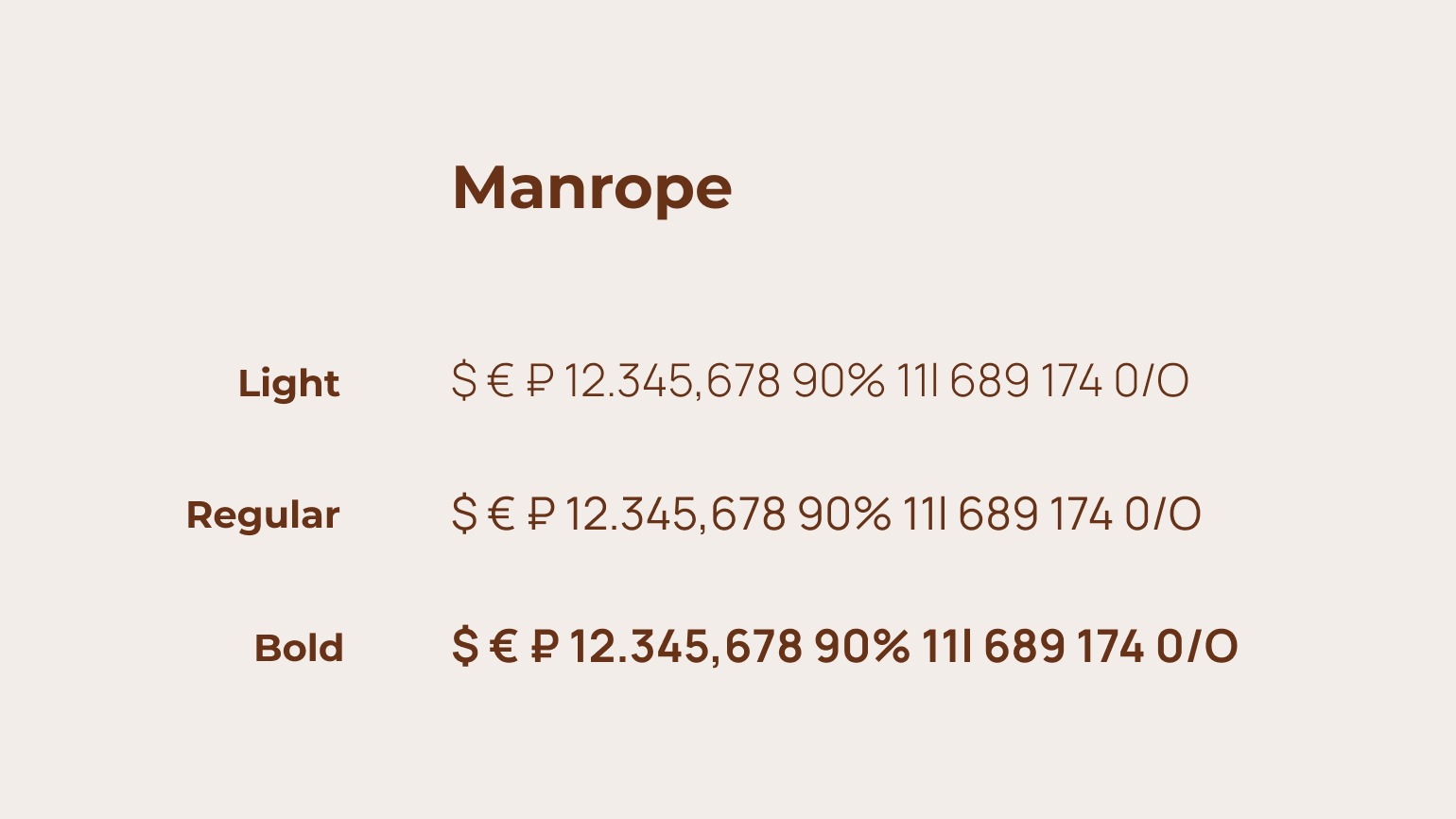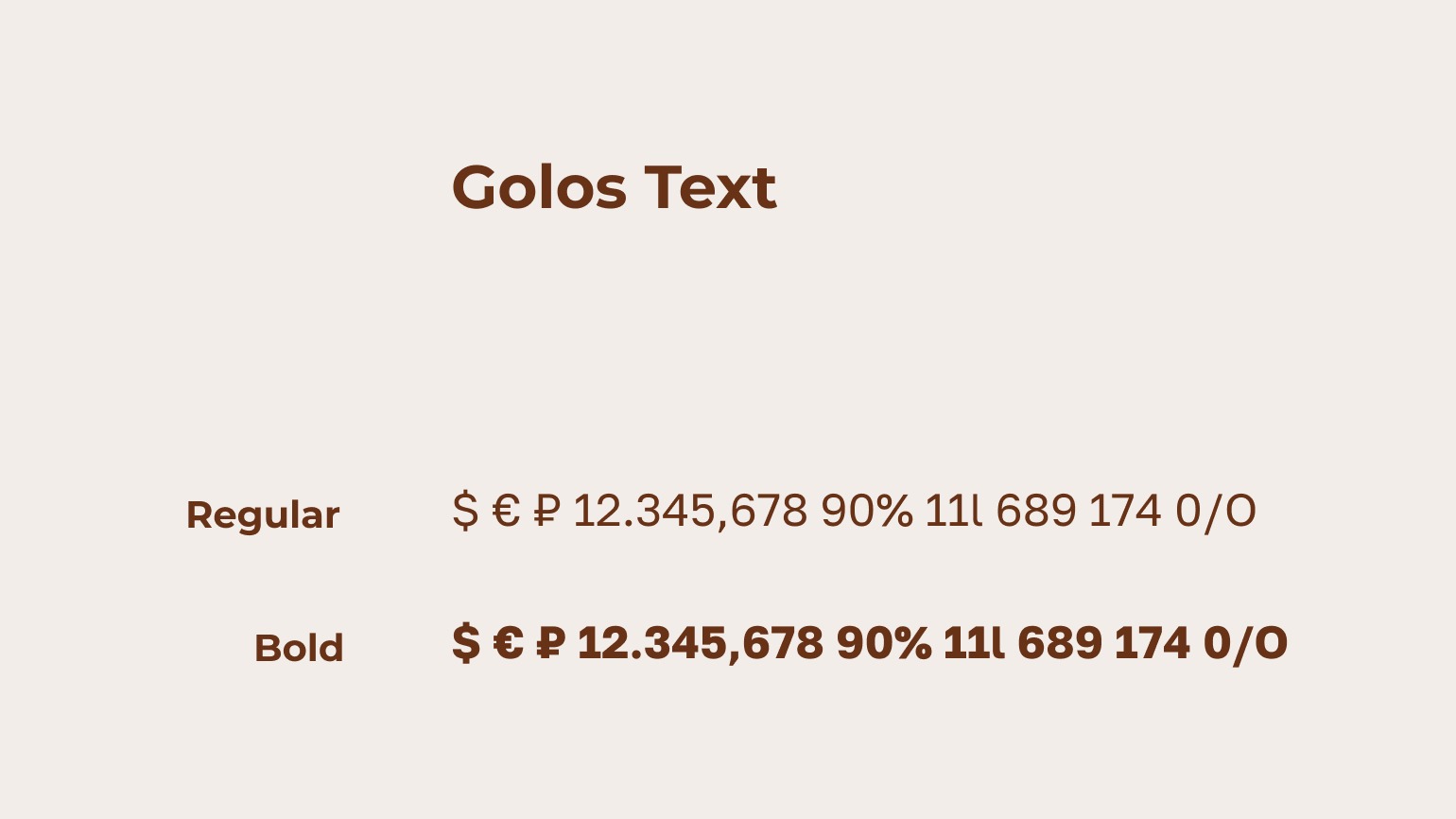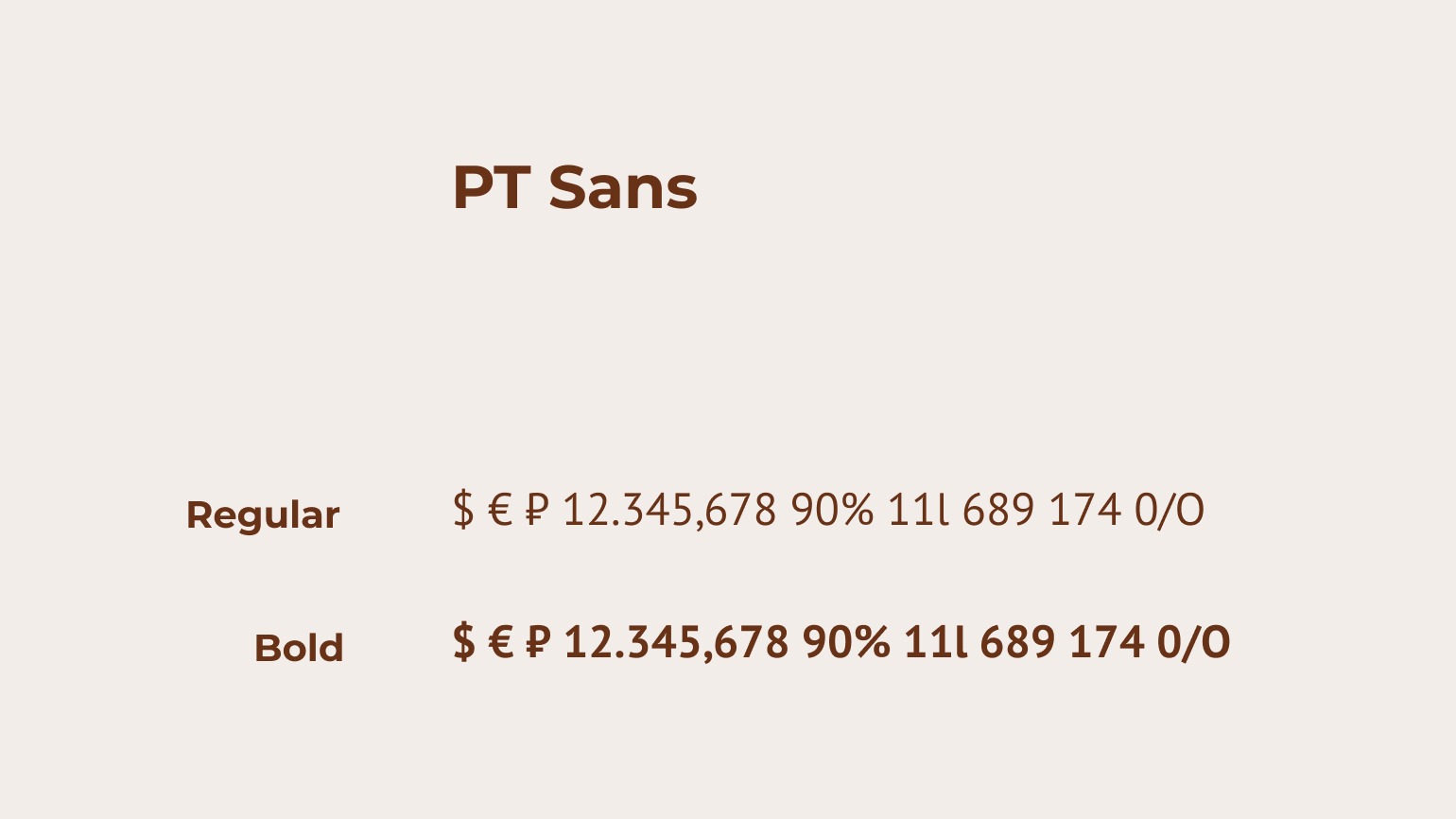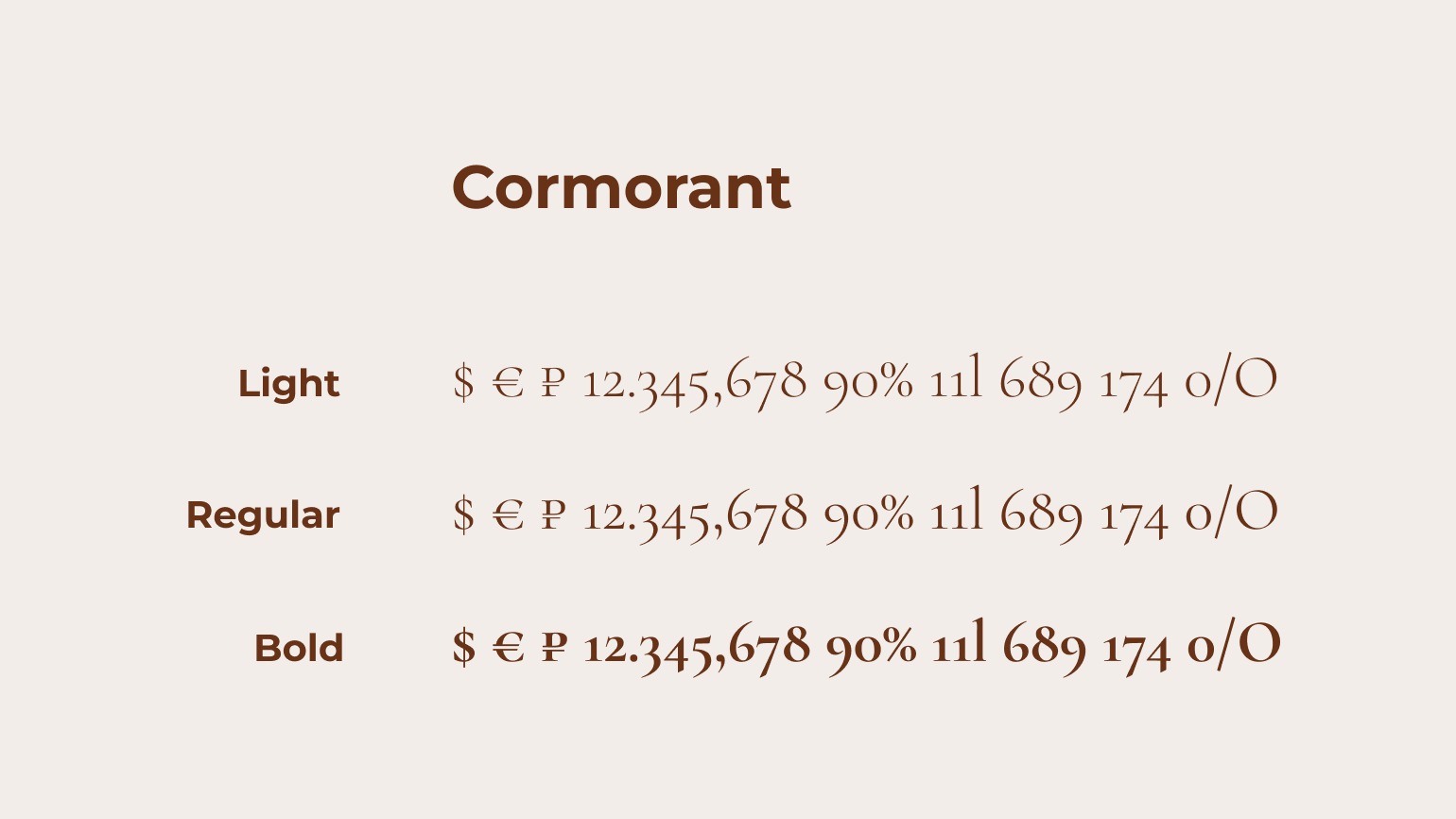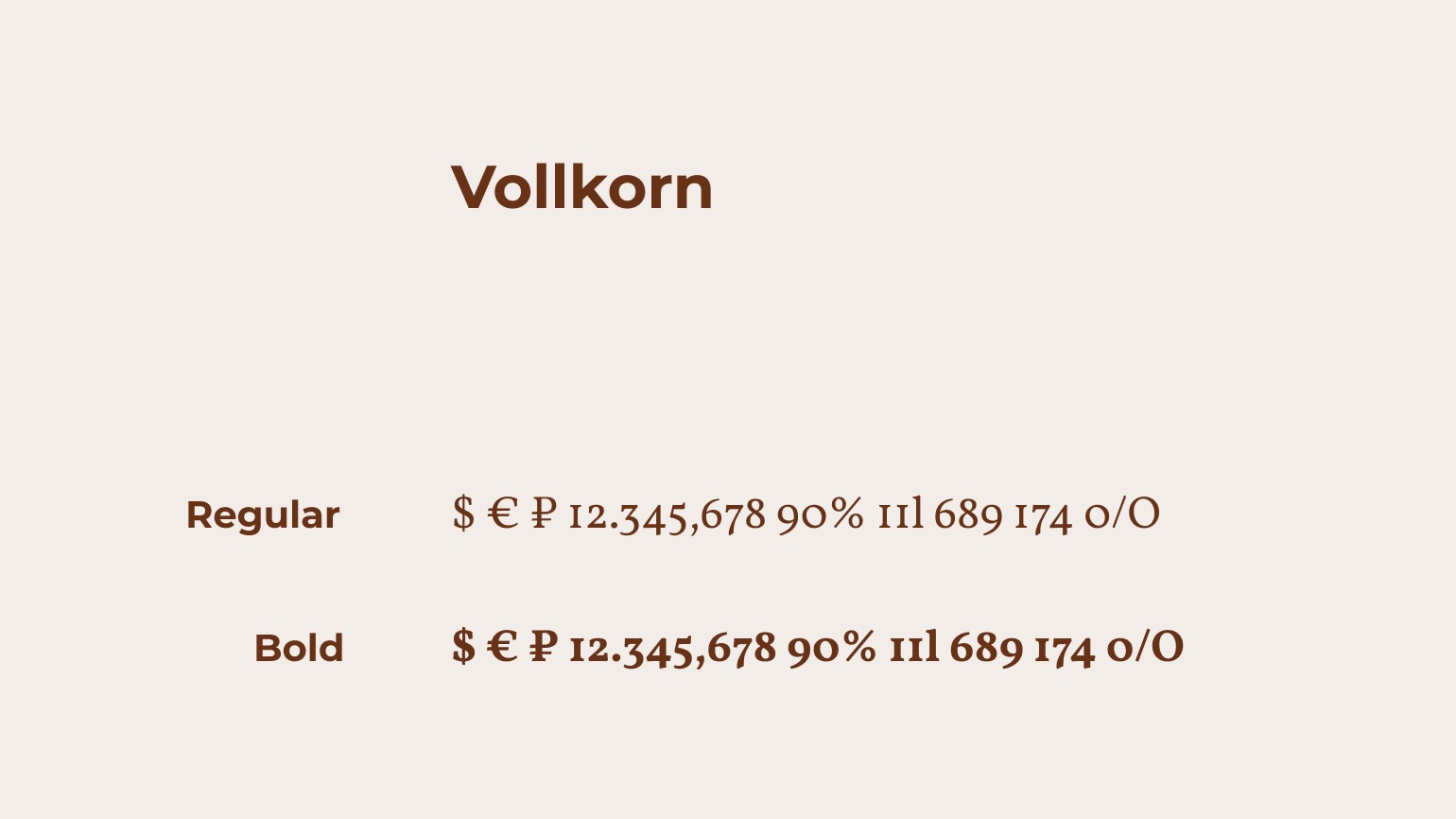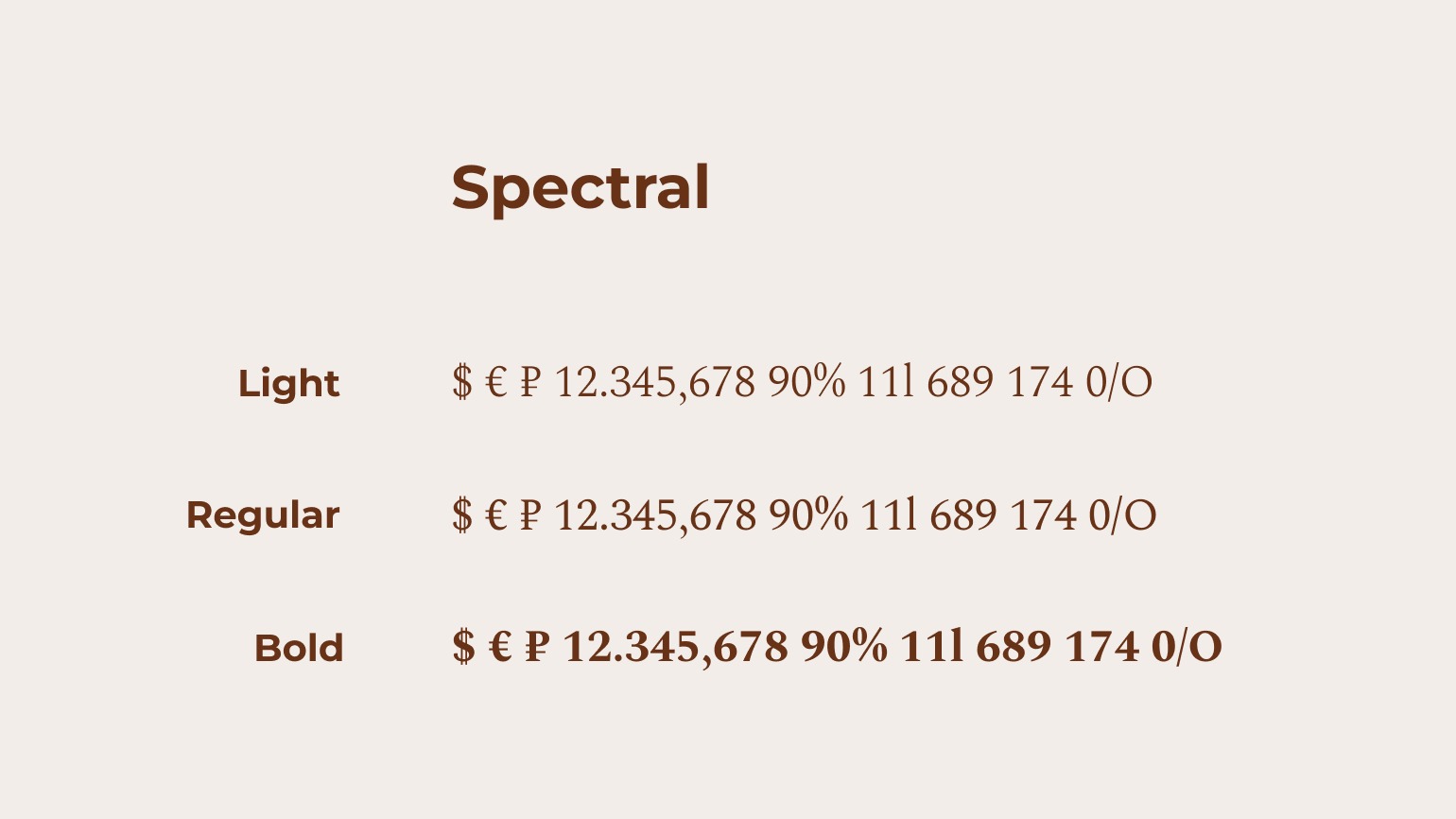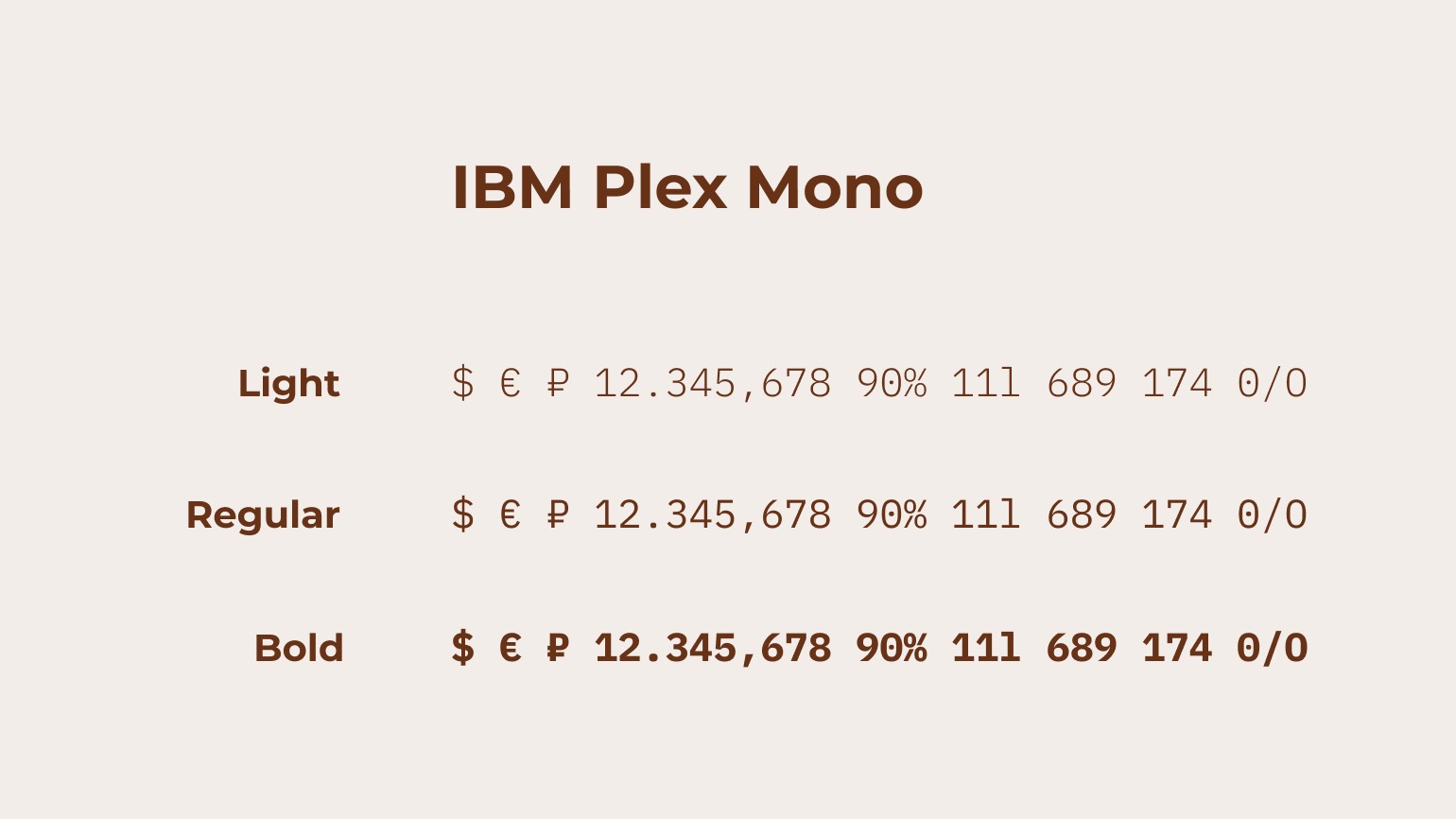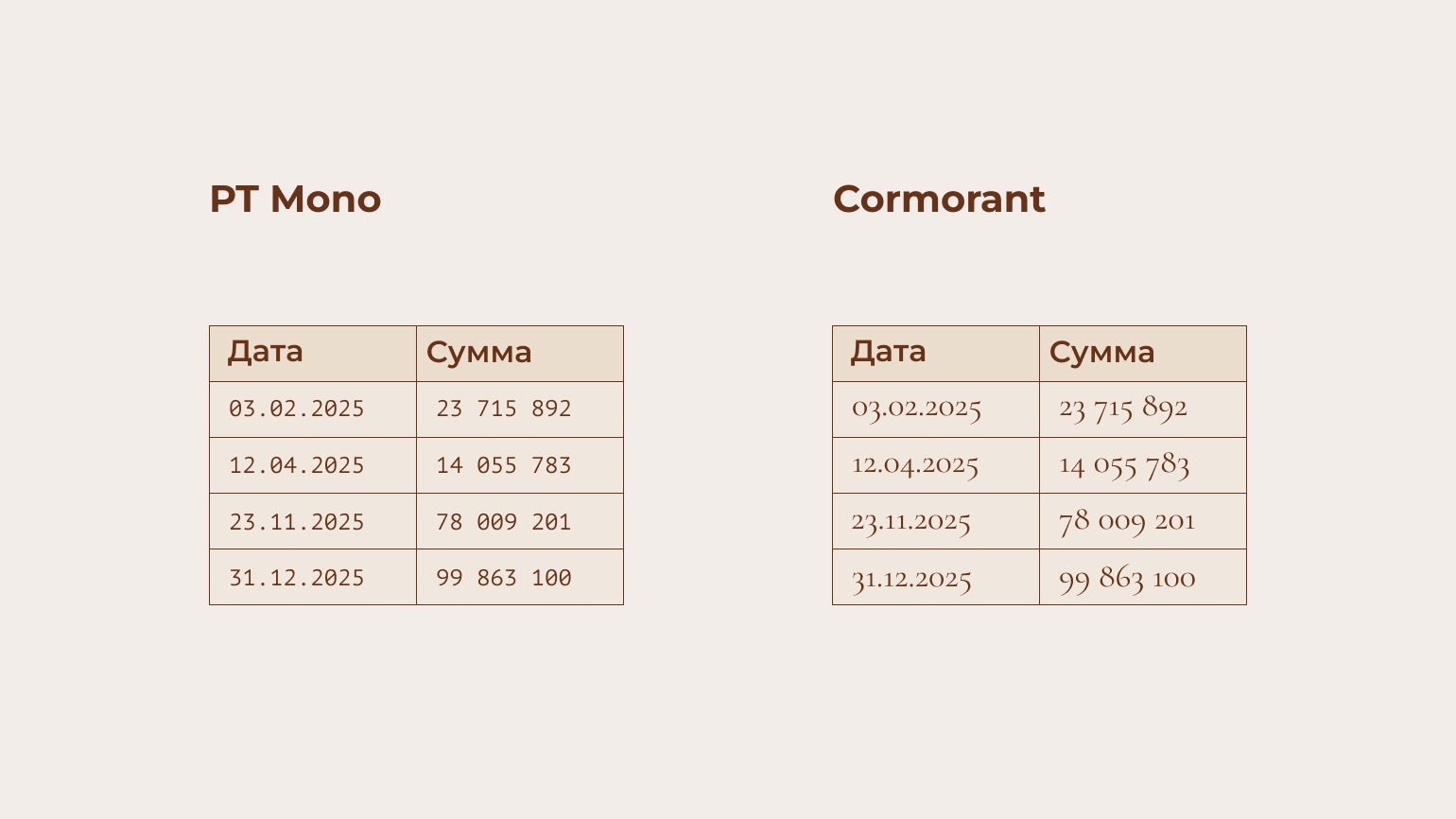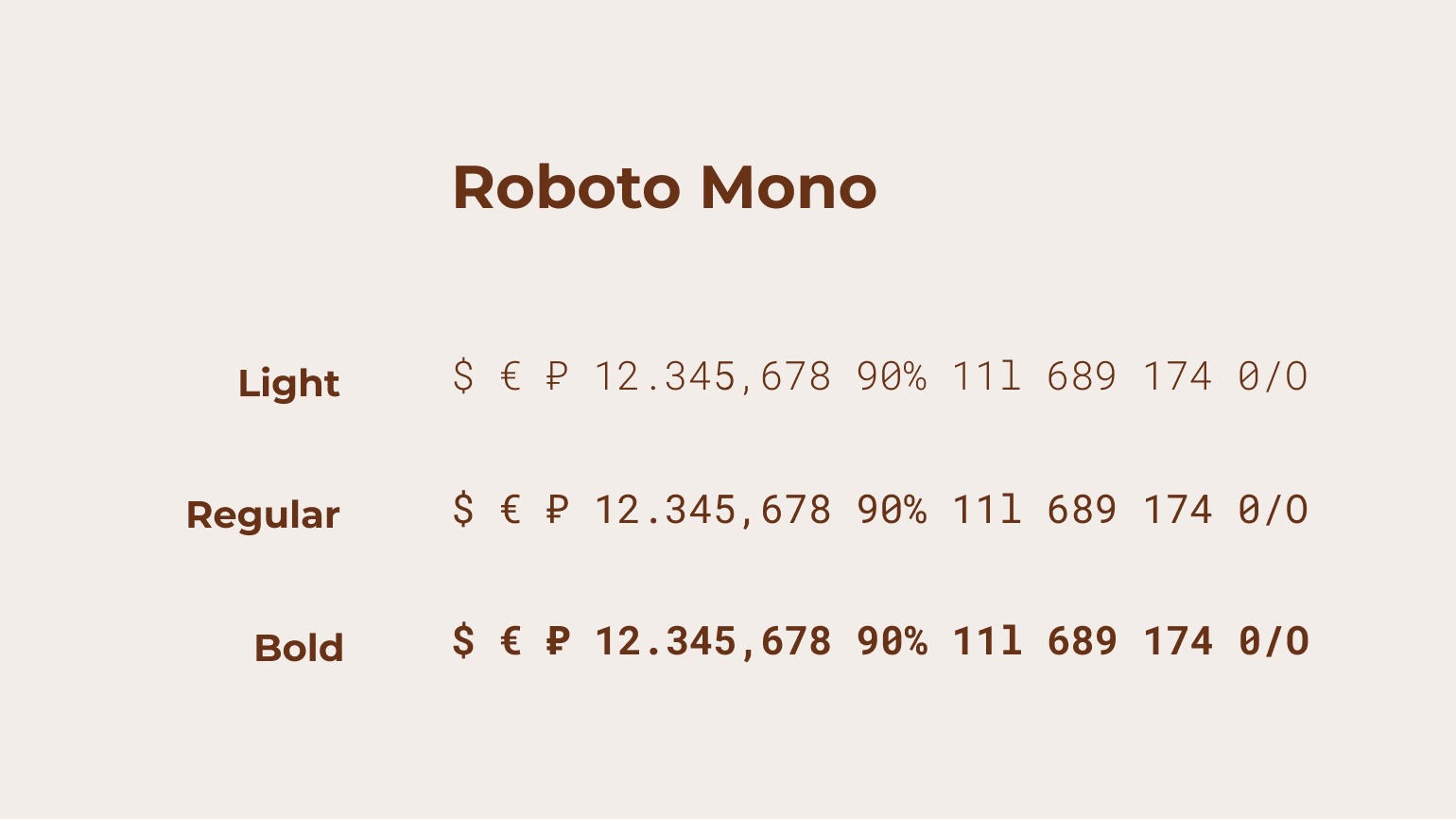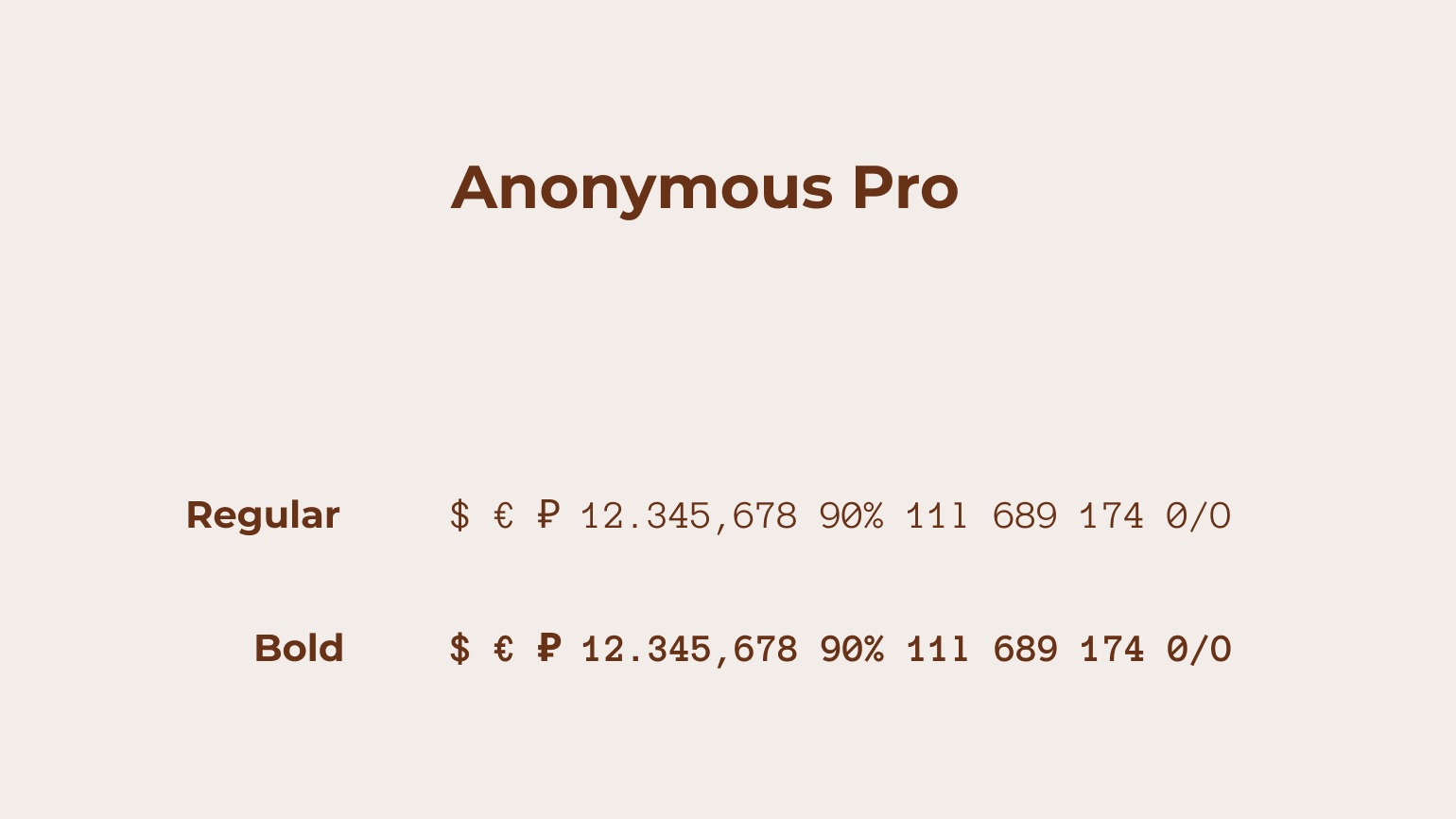
20 бесплатных красивых шрифтов для цифр и чисел
Цифры, возможно, самый недооцененный элемент типографики. Мы можем долго выбирать гарнитуру для заголовка или айдентики, но редко проверяем, как она работает с числами. А ведь именно цифры часто оказываются в центре макета: в прайсах, скидках, таймерах, аналитических дашбордах, на рекламных постерах и концертных афишах.
Поэтому вопросы вроде «как красиво написать цифры» и «где взять красивый шрифт для цифр» появляются не только у дизайнеров, но и у маркетологов, разработчиков, редакторов.
Проблема в том, что просто красивый шрифт может плохо работать с числами.
Колонки цен разваливаются и пляшут, 1 путается с латинской I, 0 — с буквой О, а 6, 8 и 9 становятся неотличимы в мелком размере.
Мы собрали 20 проверенных шрифтов, которые подойдут для серьезной работы с цифрами. Все они бесплатные и во всех есть качественная кириллица. А еще сделали мини-гайд, который поможет понять, какой шрифт подойдет для цифр именно в вашей задаче.
Как выбрать правильный шрифт для цифр и чисел
Если набрать одну и ту же дату или цену цифрами в разных шрифтах, результат может отличаться сильнее, чем кажется.
Попробуйте простой тест. Наберите выбранным шрифтом несколько строк:
0123456789
2026
−50%
11 77 55
Цифры и знаки в разных шрифтах пример
Цифры и знаки в шрифтах Montserrat и Berkshire Swash
В одних гарнитурах цифры будут выглядеть спокойно и ровно, в других — начнут вылезать за строчку, спорить между собой и терять читаемость. Это особенно заметно в интерфейсах и таблицах, где числа вписаны в колонки.
Цифры разными шрифтами в таблице
На этом примере хорошо видно, какой шрифт подходит для работы с таблицами, а какой нет
Какие бывают виды цифр в шрифтах
В типографике внешний вид цифр шрифта определяют два основных параметра — ширина и высота. По ширине цифры могут быть:
— табличными — все одинаковой ширины;
— пропорциональными (1 — очень узкая, 0 — широкая, 8 — еще шире).
По высоте цифры могут быть:
— линейными — в этом случае их высота равна строчным буквам, а сами цифры аккуратно вписаны в строку;
— старостильными — высота цифр равна прописным буквам, а сами они выглядят скорее декоративно и выходят за верхнюю и нижнюю границу строки.
Из комбинации этих параметров образуются четыре основных типа цифр в шрифтах.
1. Tabular Lining — табличные линейные цифры
В этом варианте все цифры одной высоты, одинаковой ширины, стоят строго по сетке. Табличные линейные цифры подходят для таблиц, финансовых отчетов, дашбордов, прайсов, интерфейсов. Если вам нужно, чтобы колонка цен выглядела идеально ровно, — используйте именно их.
Табличные линейные цифры пример
Табличные линейные цифры — одинаковой высоты и одинаковой ширины
2. Proportional Lining — пропорциональные линейные цифры
Это самый распространенный вариант цифр в современных шрифтах. Все цифры в пропорциональном линейном варианте одинаковой высоты, но разной ширины. Используйте их, если вам нужно добавить цифры в заголовок, инфографику, баннер, сделать акцентный числовой элемент в интерфейсе.
Пропорциональные линейные цифры пример
Пропорциональные линейные цифры — одинаковой высоты, разной ширины
3. Proportional Oldstyle — пропорциональные старостильные цифры
Такие цифры называют еще минускульными. Они ведут свое графическое происхождение от рисунка древних арабских цифр. Минускульные цифры отличаются и по высоте, и по ширине, а по характеру ближе скорее к буквам, чем к цифрам. Используют их чаще всего в большом массиве текста: книгах, журналах.
Пропорциональные старостильные цифры пример
Пропорциональные старостильные цифры — разные по ширине и разные по высоте
4. Tabular Oldstyle — табличные старостильные цифры
У табличных старостильных цифр разная высота (как у минускульных), но одинаковая ширина, как у табличных. Их выбирают, если нужен компромисс между табличной простотой и типографической выразительностью. Шрифты с такими цифрами встречаются редко, иногда их можно включить через OpenType-функции, но это зависит от конкретной версии шрифта.
Табличные старостильные цифры можно найти в научных публикациях, старинных и стилизованных под старину изданиях. Например, в сборниках математических таблиц начала прошлого века.
Табличные старостильные цифры, пример, старый советский справочник
Страница из книги. Асатиани Л. Г. Карманные таблицы умножения и деления для экономистов, инженеров, бухгалтеров, агрономов и пр. М., Л., Государственное издательство, 1930
20 бесплатных шрифтов с красивыми цифрами
Мы выбрали 20 бесплатных гарнитур с кириллицей, в которых цифры выглядят аккуратно и читаемо. Этот набор позволяет подобрать правильный стиль цифр для самых разных задач: интерфейсов, инфографики, плакатов и таблиц.
Каждый шрифт проверяем в нескольких начертаниях набором основных символов: знаки валют и процентов, точка, запятая, слеш, все цифры. Кроме того, смотрим, насколько отличаются друг от друга:
Почему в одном шрифте цифры могут выглядеть по-разному?
Потому что в гарнитуре могут быть разные наборы цифр — табличные (tabular), пропорциональные (proportional), старостильные (oldstyle).